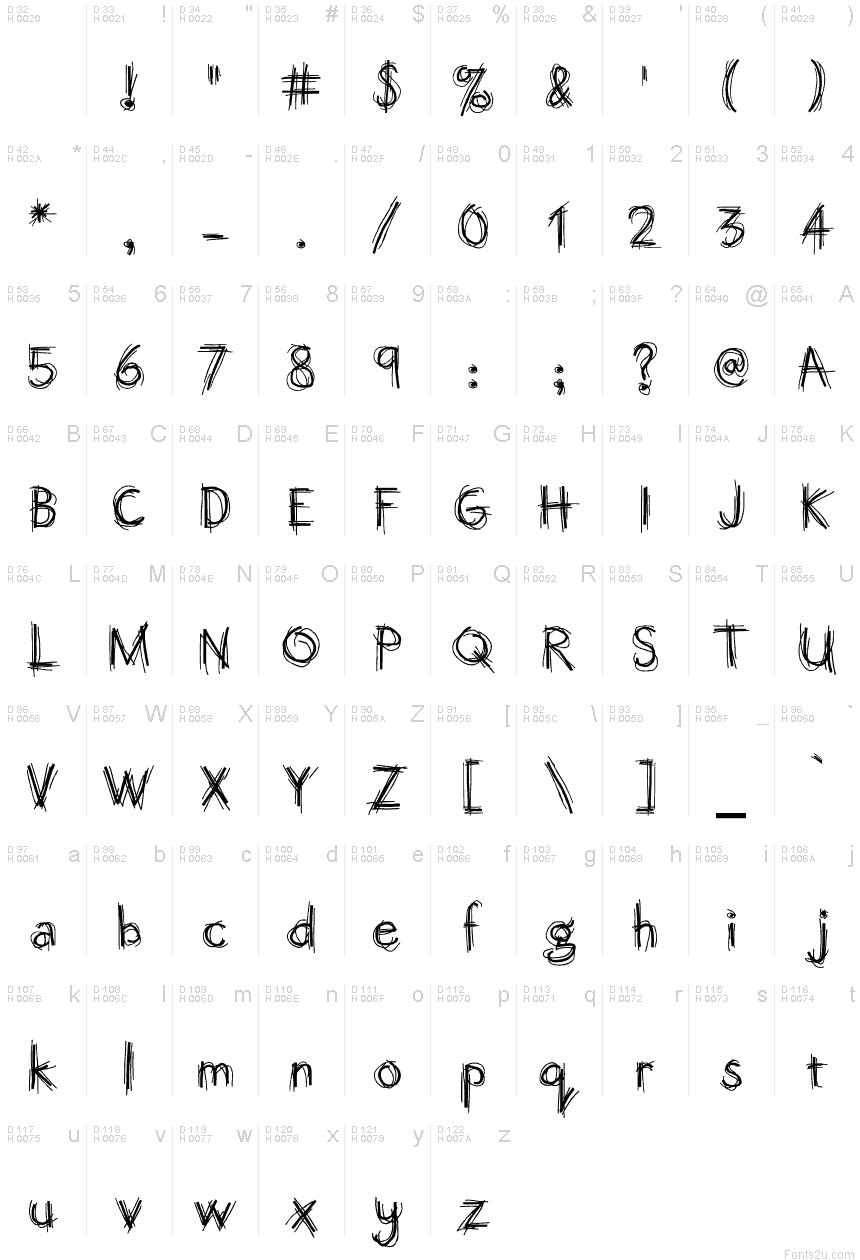
Octember Script to darmowy font typu display w stylu trash, charakteryzujący się luźnymi, odręcznymi konturami i wielokrotnymi zadrapaniami, które nadają literom niespokojny, improwizowany charakter. Krzywe pozostają okrągłe i elastyczne, a kreski łamią się i krzyżują, zamiast układać się w schludny obrys.
Ta surowa, szkicowa tekstura świetnie sprawdzi się w tytułach plakatów, zinach, okładkach albumów, ulotkach czy w brandingu DIY, który ma mieć charakter „z pazurem”. Pasuje również do grafik w klimacie horroru, promocji muzycznych i streetwearu, gdzie nierówna linia nadaje całości osobistego, niepodrabialnego wyrazu.